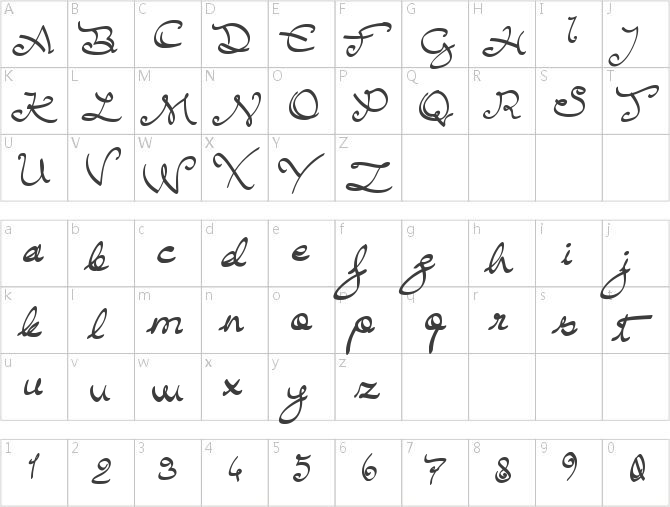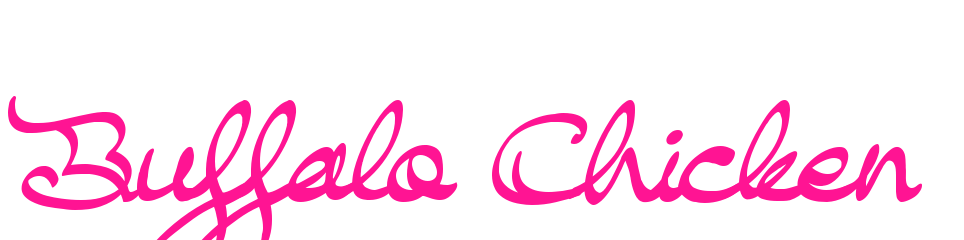
字體名稱: Buffalo
Buffalo Chicken
Buffalo Chicken字體字庫(kù)是一款讓人賞心悅目、百看不厭的英文字體,適合各類廣告和產(chǎn)品包裝設(shè)計(jì)應(yīng)用,字體大小0.05MB,格式為ttf字體,上傳用戶是happy,作者/版權(quán)方為未知